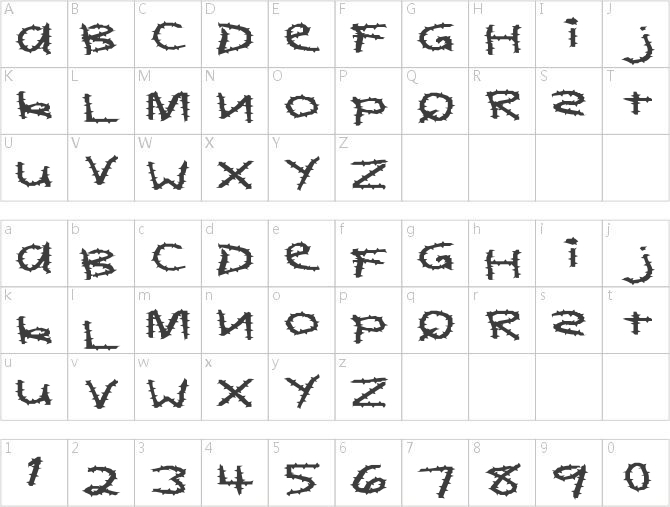
FZ HAND 11 SPIKED EX 詳情頁
FZ HAND 11 SPIKED EX字體字庫是一款讓人賞心悅目、百看不厭的英文字體,適合各類廣告和產(chǎn)品包裝設(shè)計(jì)應(yīng)用,字體大小0.06MB,格式為ttf字體,上傳用戶是洛洛,作者/版權(quán)方為未知